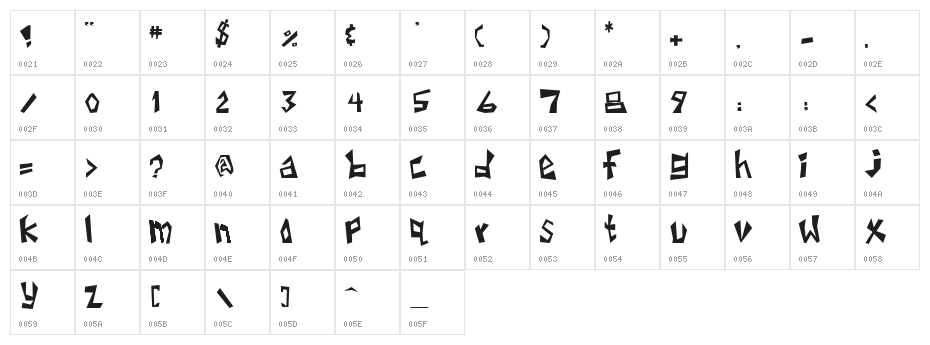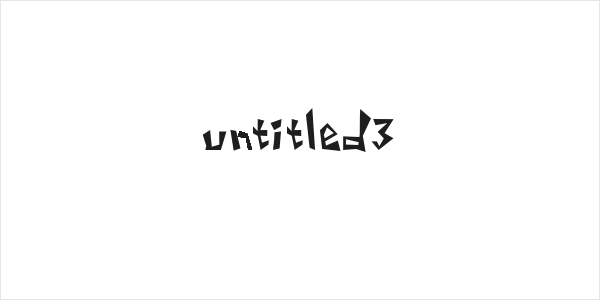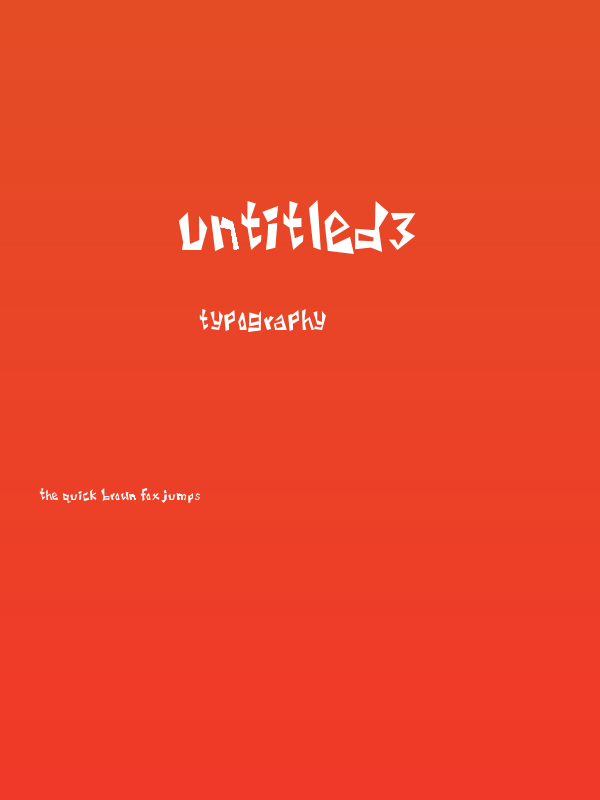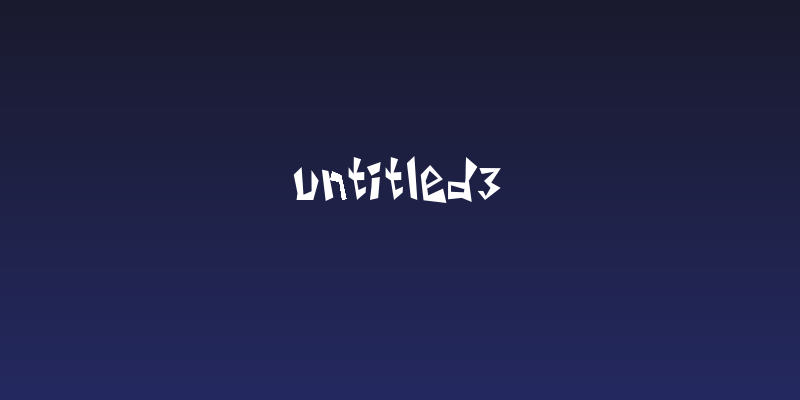
untitled3 Font
| Progetti proposti | Ideal for album covers, posters, branding for edgy or modern products, and any design needing a bold, artistic touch. |